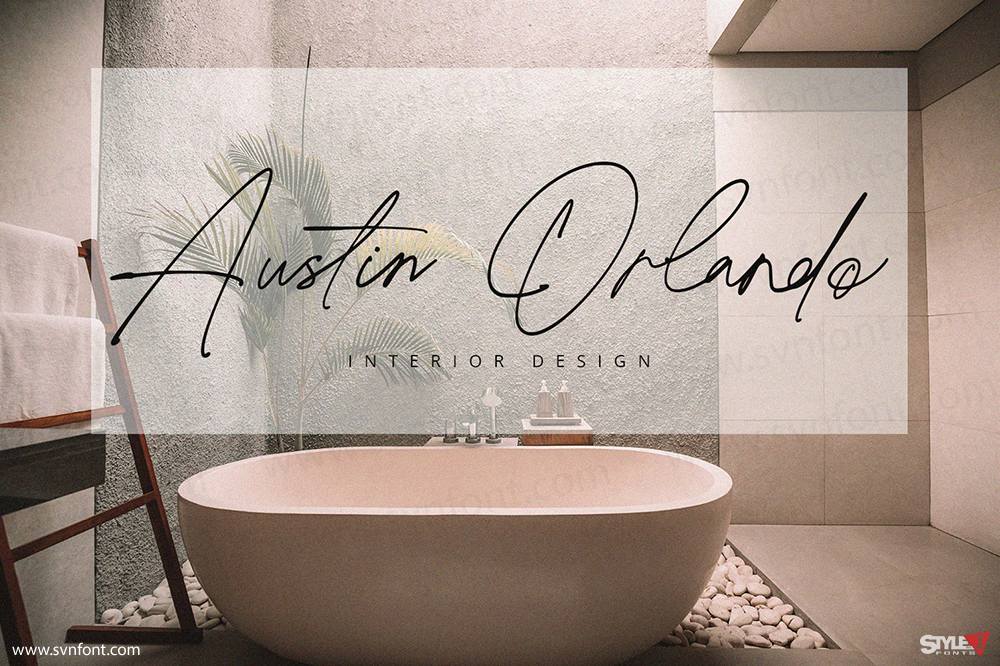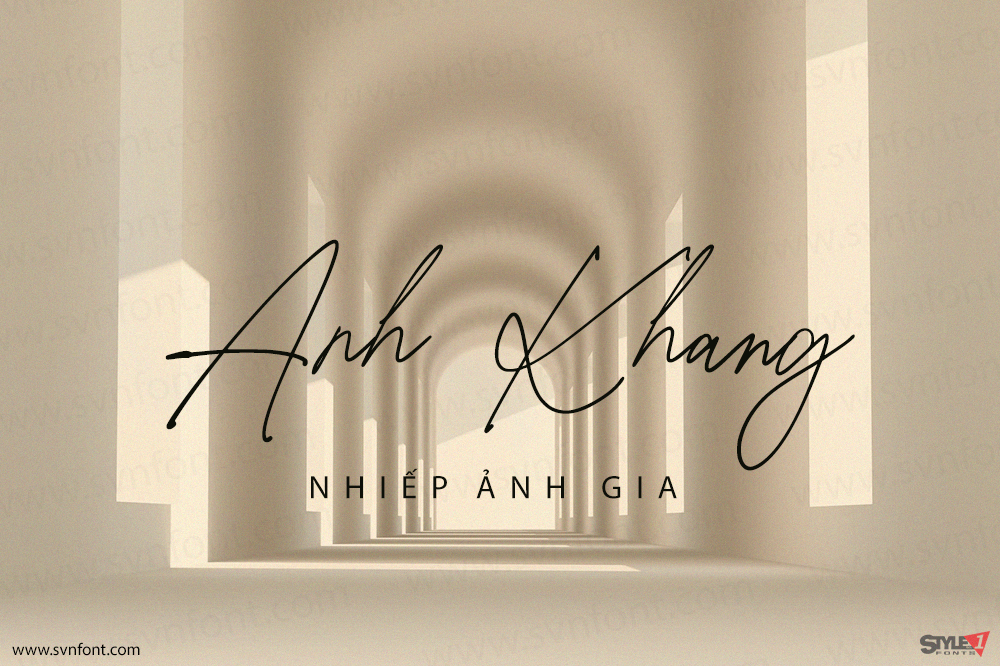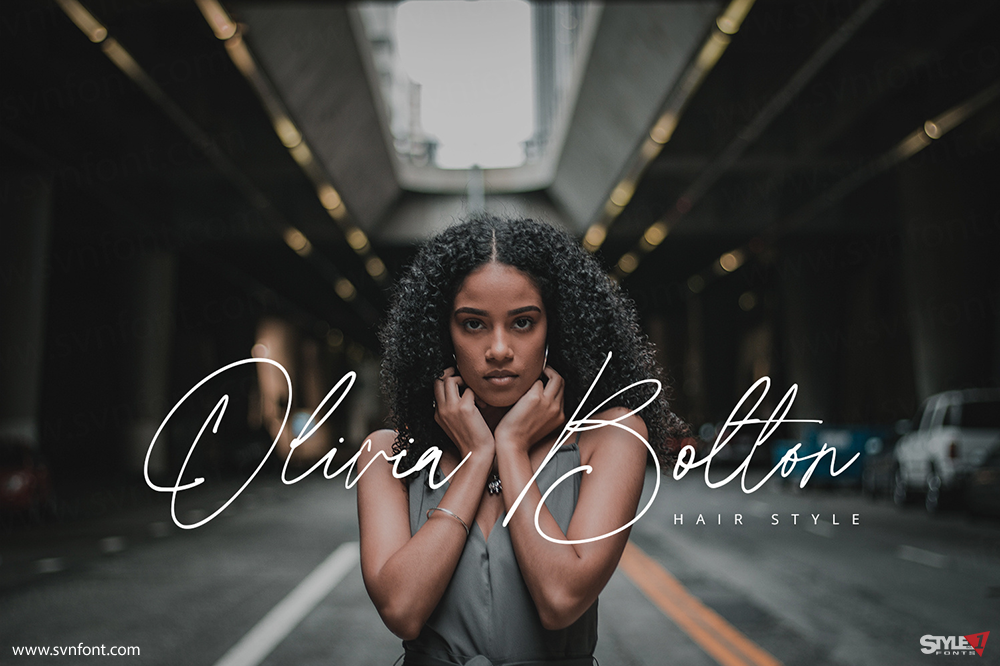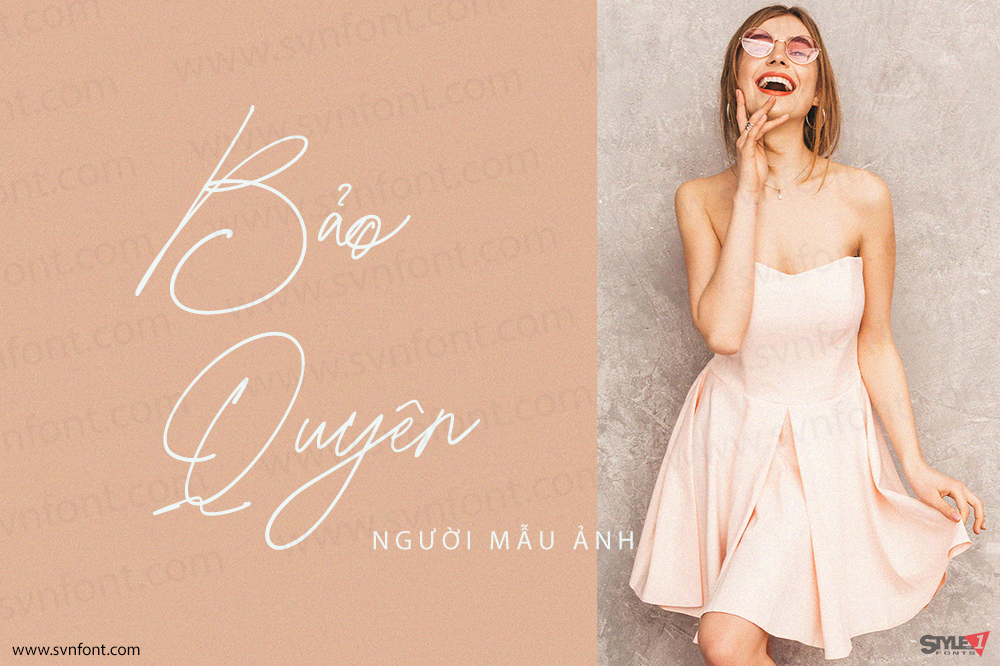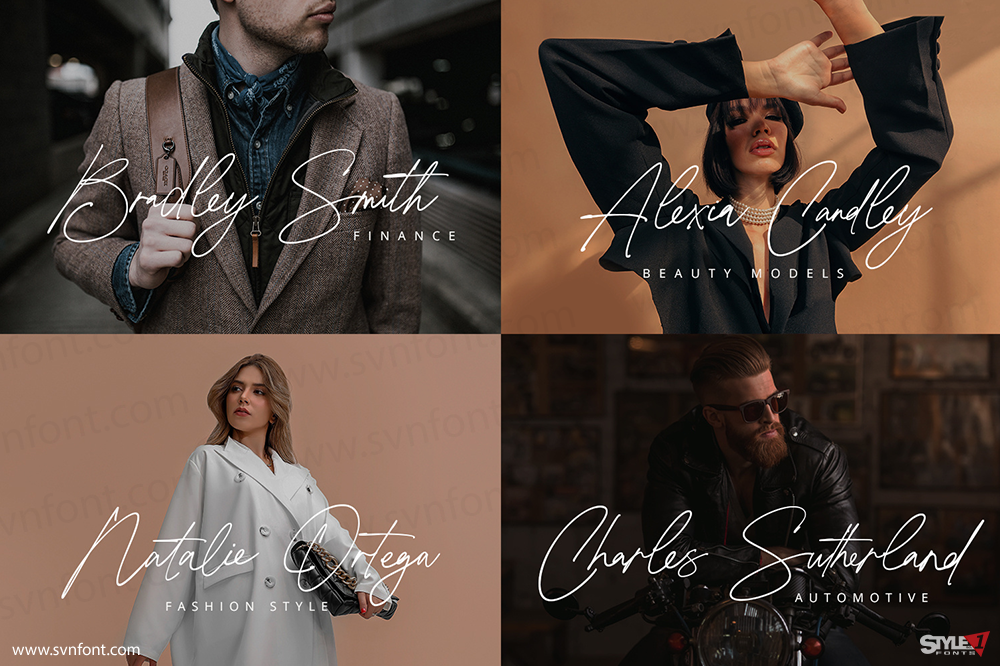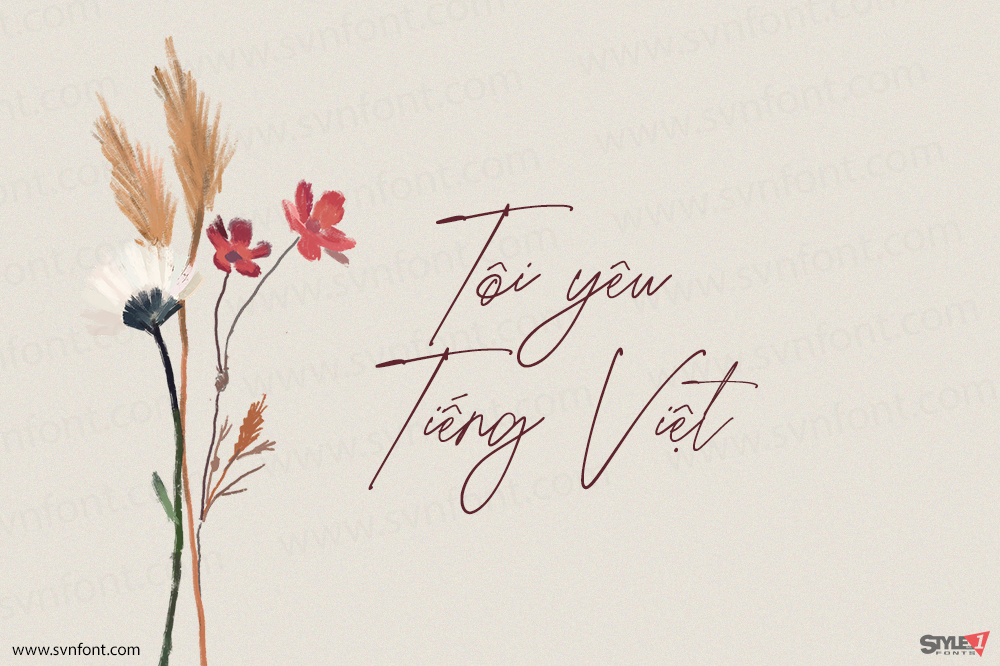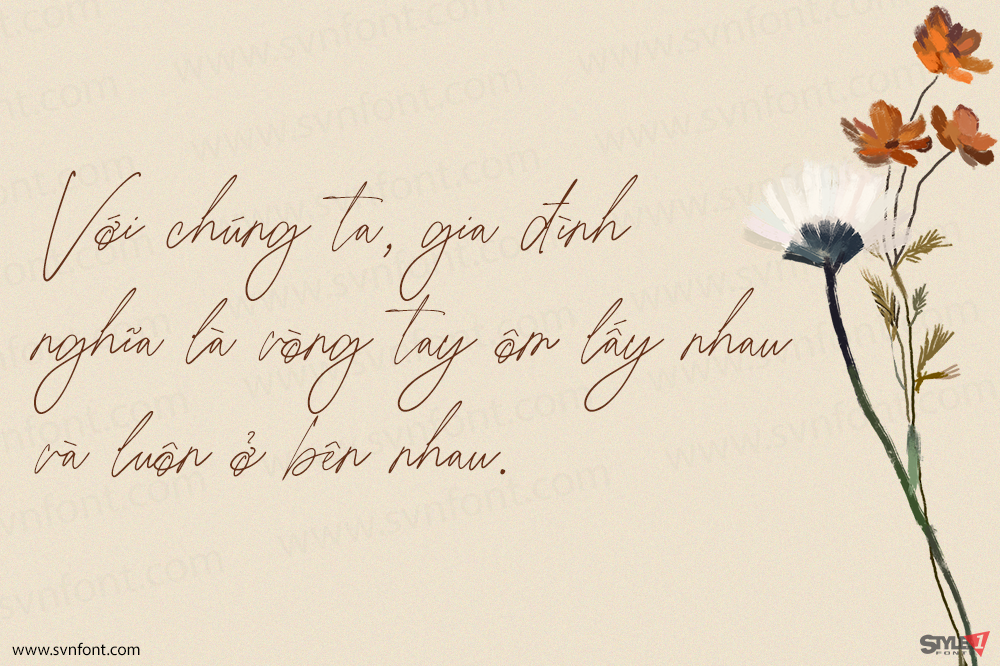
Betalisa là một font chữ ký đầy phong cách với cảm giác chân thực và phóng khoáng. Font này sẽ được sử dụng hoàn hảo cho việc xây dựng thương hiệu, thiết kế logo, chữ viết tay, logotype, quần áo, áp phích, tạp chí, bao bì, túi mua sắm, áo thun, bìa sách, nhiếp ảnh, các sự kiện đặc biệt và các dự án thiết kế khác.